El lettering victoriano o el tipo de letra victoriana, como su nombre indica, tiene su origen en la era victoriana, es decir, durante el reinado de la la reina Victoria de Inglaterra, entre 1837 y 1901. En esa época, tuvieron lugar dos acontecimientos que marcaron mucho a la sociedad y el arte: la Revolución Industrial y la Gran Exposición en el Crystal Palace de Londres.
ORIGEN DEL LETTERING VICTORIANO
La letra victoriana está muy influenciada por el estilo arquitectónico de la época, principalmente marcado por el Palacio de Cristal o Crystal Palace de Londres construido en 1851, donde el hierro y el vidrio estaban muy presentes, así como que se tienen en cuenta las decoraciones y las formas coquetas. Entonces, la letra victoriana, tiene también esta apariencia metálica con texturas y con elementos decorativos, y se utilizaba mucho en rotulación de comercios mediante el grabado en metal, en madera o en cristal, así como en cartelería impresa. A continuación vamos a ver un par de ejemplos de lettering victoriano de la época.
En este ejemplo vemos claramente varios tipos de lettering victoriano original. Como podemos leer, es una publicidad de «A. Hoen & Co.», que precisamente eran litógrafos, diseñadores, grabadores e impresores de la época victoriana.
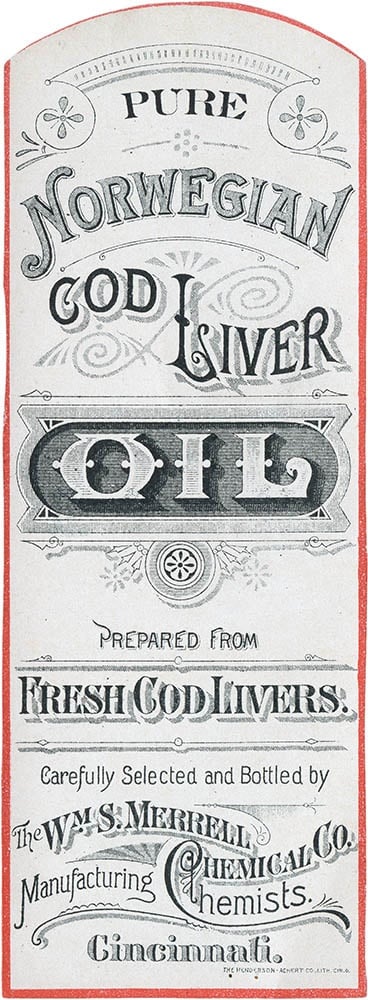
Otro ejemplo de lettering victoriano lo vemos en este anuncio de «Norwegian Cod Iver Oil», también diseñado con varios tipos de letra victoriana, cada una con una característica peculiar.
CARACTERÍSTICAS DEL LETTERING VICTORIANO
- Sus letras son bellas, tienen mucha personalidad, con un estilo muy marcado que puede reconocer.
- Se inspira en estampados, florituras y ornamentaciones que decoraban el hand lettering o letra dibujada a mano de épocas anteriores, como la Edad Media y el Renacimiento, como las iniciales de los manuscritos.
- Sus astas pueden ser finas, medias o gruesas, lo importante es que estén estilizadas.
- Tiene decoraciones y florituras, tanto en medio de la asta, como en los remates.
- Suelen ser siempre letras mayúsculas, aunque la primera letra es más grande que el resto, es decir, en versalitas.
- Sus letras tienen texturas que imitan el trabajo manual sobre madera, metal o cristal.
- Es frecuente ver sombreados en negro o en gris muy efectistas.
ALFABETO LETTERING VICTORIANO
EL LETTERING VICTORIANO ESTÁ DE MODA
Hoy en día hay muchos diseñadores y artistas, David Smith es el más destacado, que han recuperado el lettering victoriano para la rotulación de negocios, especialmente aquellos que tienen algo de tradición y artesanía, como puede ser una barbería, una tienda de licores o un estudio de tatuajes. Tanto sus dibujos de letras victorianas a mano, como sus grabados con pan de oro sobre el cristal de comercios, es absolutamente alucinante y os dejamos una muestra de ello.